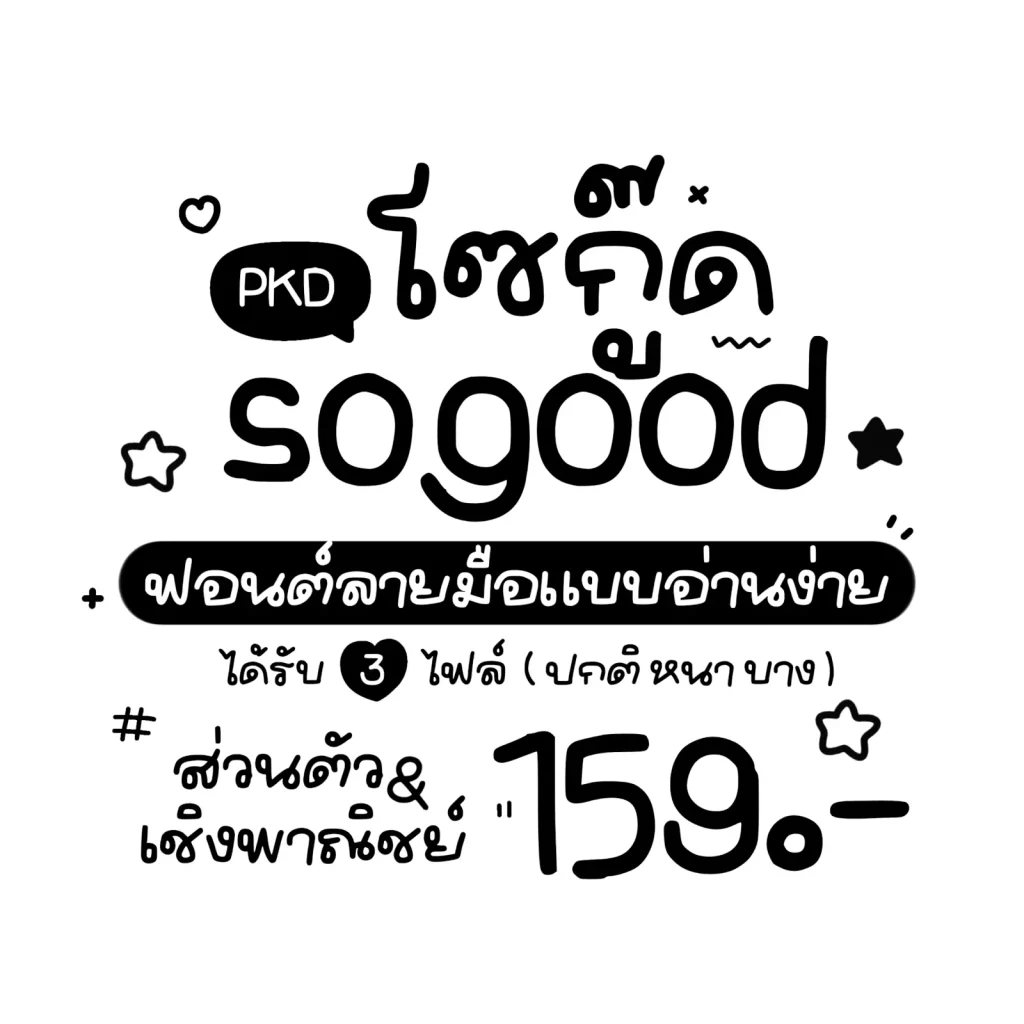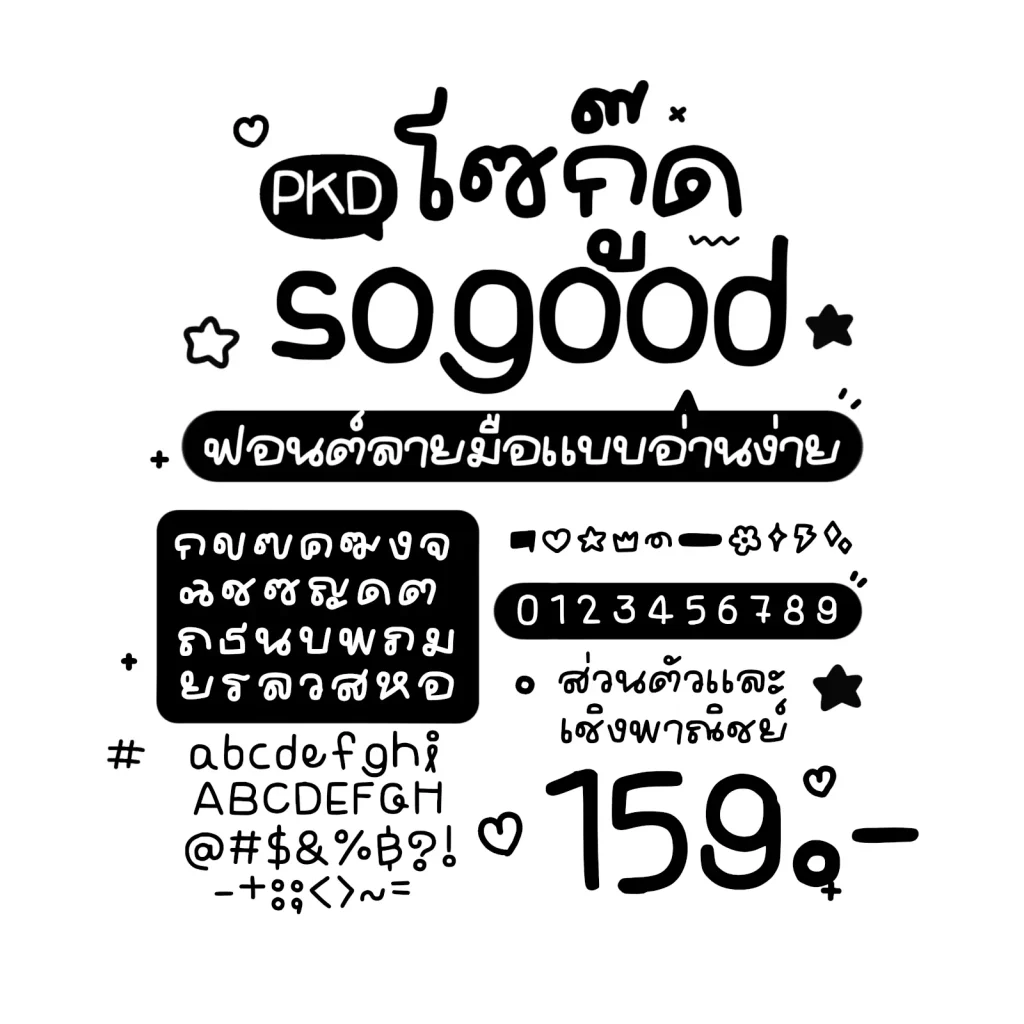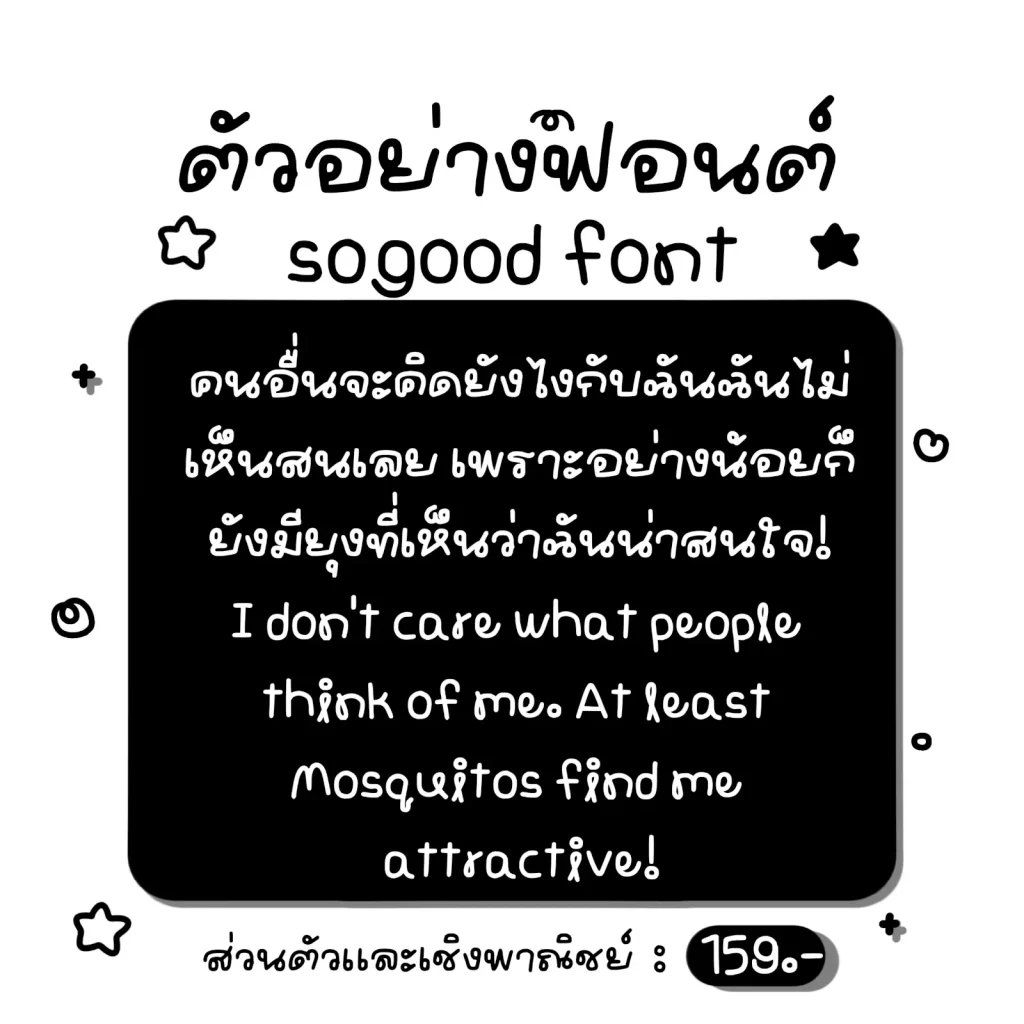
โซกู๊ดฟอนต์ (PKD SOGOOD) – ฟอนต์ลายมือน่ารัก สดใส เป็นกันเอง เหมาะสำหรับงานคอนเทนต์ โพสต์โซเชียล สติกเกอร์ คาเฟ่ และงานออกแบบทั่วไป
- มีตัวอักษรโปร่งผสมในบางตำแหน่ง
- ไม่มีตัวอักษรโปร่งผสม
- รองรับภาษาไทย ภาษาอังกฤษ ตัวเลข และสัญลักษณ์
โซกู๊ด (PKD SOGOOD)